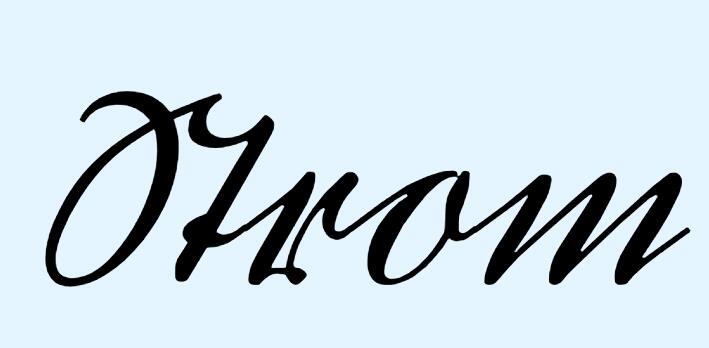
Wer kann helfen - Wort im deutschen Text 2. Weltkrieg
dieser Text schrieb ein Soldat während des 2. Weltkrieges.
"Wann wird das Ungeheuer "Krieg" seine feurigen Arme über den ___ werfen? Wann flammt es.."
Ich kann das erste Wort in der 3. Zeile nicht wirklich erkennen. Was lesen Sie?
Ich dachte selber an Sturm oder Stern. Das würde mehr Sinn machen.
Wobei der Schreiber das 'u' meistens mit einem Strich drüber andeutete (hier eben nicht) und das 't' in Stern ist auf zwei verschiedene Arten geschrieben.
Ich habe wie gebeten noch ein paar Schriftproben hinzugefügt.
Und vielleicht finden Sie auch gleich die 'Lösung' des 2. Teile von dem Wort 'Kampf..'
*Tekst Ruhe vor dem Sturm
Es ist die ruhe vor dem Sturm!
*Text Sowjet-Stern
Wir werden den Kampfmut/durst (?) bald kennenlernen. Es kämpft dann das Hakenkreuz gegen den Sowjet-Stern. Zwei Weltan-schauungen stoßen zusammen.
Für mich sieht die Glyphenkombination St in »Sturm« und »Stern« anders aus als im ersten Dokument. Könnte da vielleicht ein Flussname gemeint sein wie Nare? Ich hab das jetzt nicht entziffert, sondern rate nur (cave confirmation bias!)
Der Schreiber hat diesen Eintrag wohl an einem Fluss gemacht (das Stück also richtig geraten), das war jedoch der Bug. Ich denke dass dann doch 'Strom' das richtige Wort sein könnte.